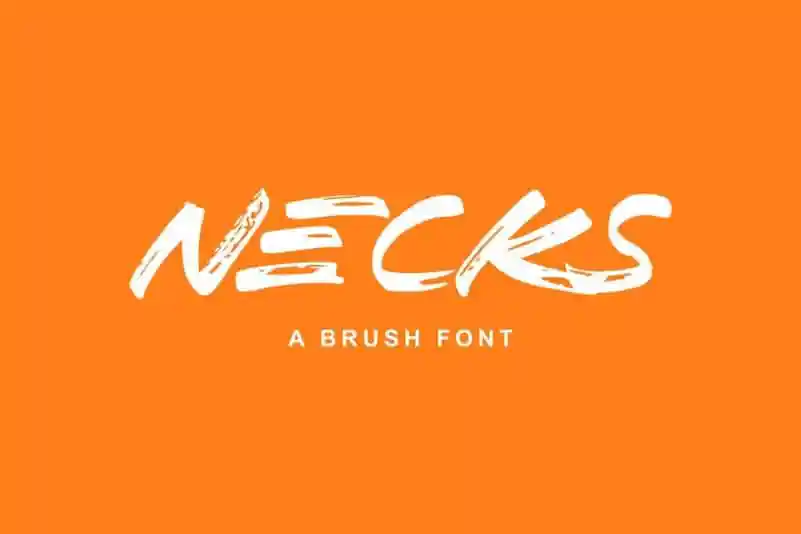
A Necks Brush Font é uma elegante tipografia feita para aqueles que buscam algo mais além dos padrões tradicionais. Ela oferece um toque único ao combinar a elegância das fuentes escritas à mão com a força e os detalhes acintosos de uma fonte desenhada com o auxílio de uma caneta-pen. Este tipo em letras grandes é perfeito para logomarcas, identidades corporativas e mensagens, trazendo um toque criativo e único aos projetos de design. Feita pelo designer Andika Fez, a Necks Brush Font é o elemento ideal para aqueles que querem dar uma aparição única em seus trabalhos de design. Sua aparência bold e acintosa cria um efeito vibrante nas suas obras, tornando-a perfeita tanto para se utilizar em logotipos ou branding quanto para personalizar mensagens de citações com personalidade. Adicione a Necks Brush Font à sua galeria de ideias criativas e inspire-se com uma fonte que oferece um toque único e impecável. Ela certamente será o toque final perfeito para qualquer projeto gráfico ou design visual, garantindo sempre uma aparição memorável.